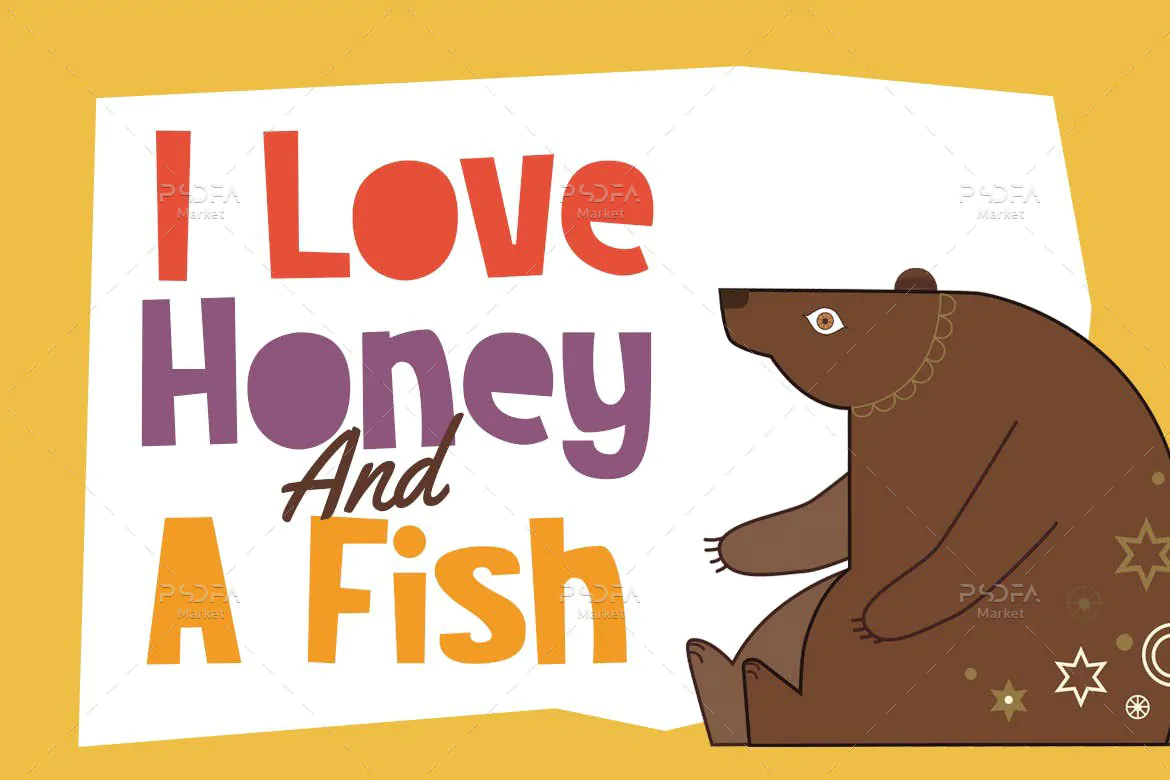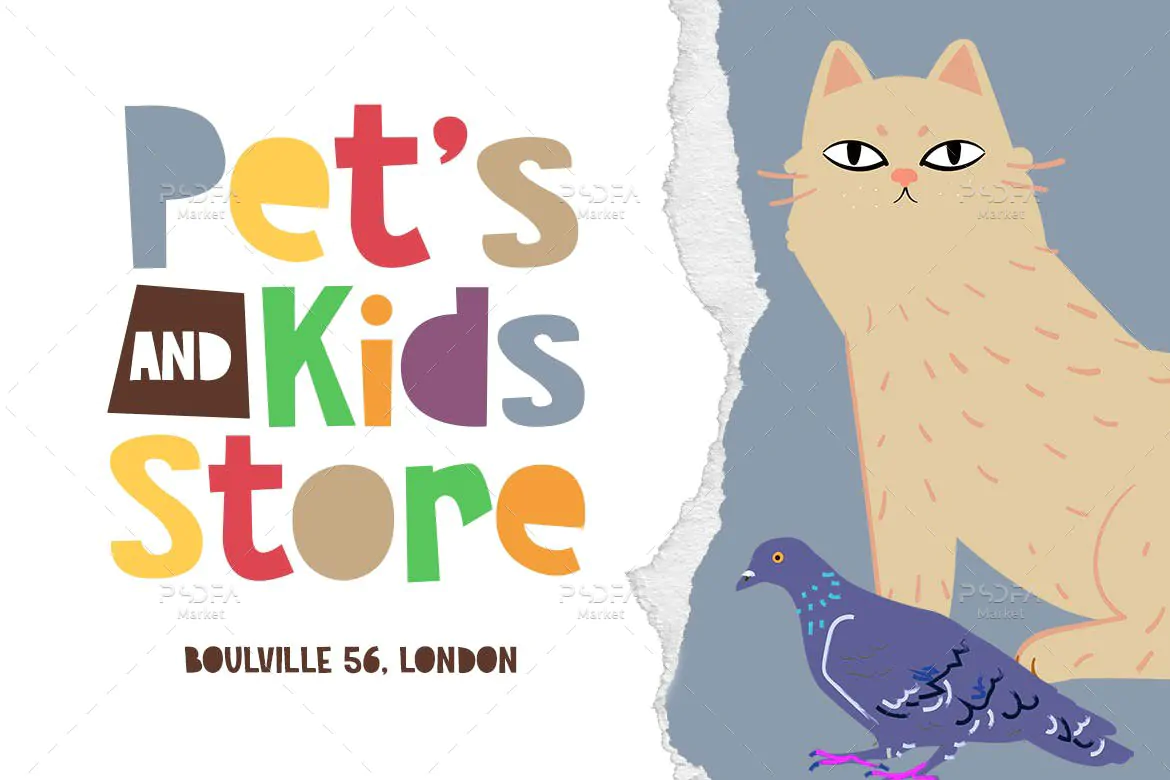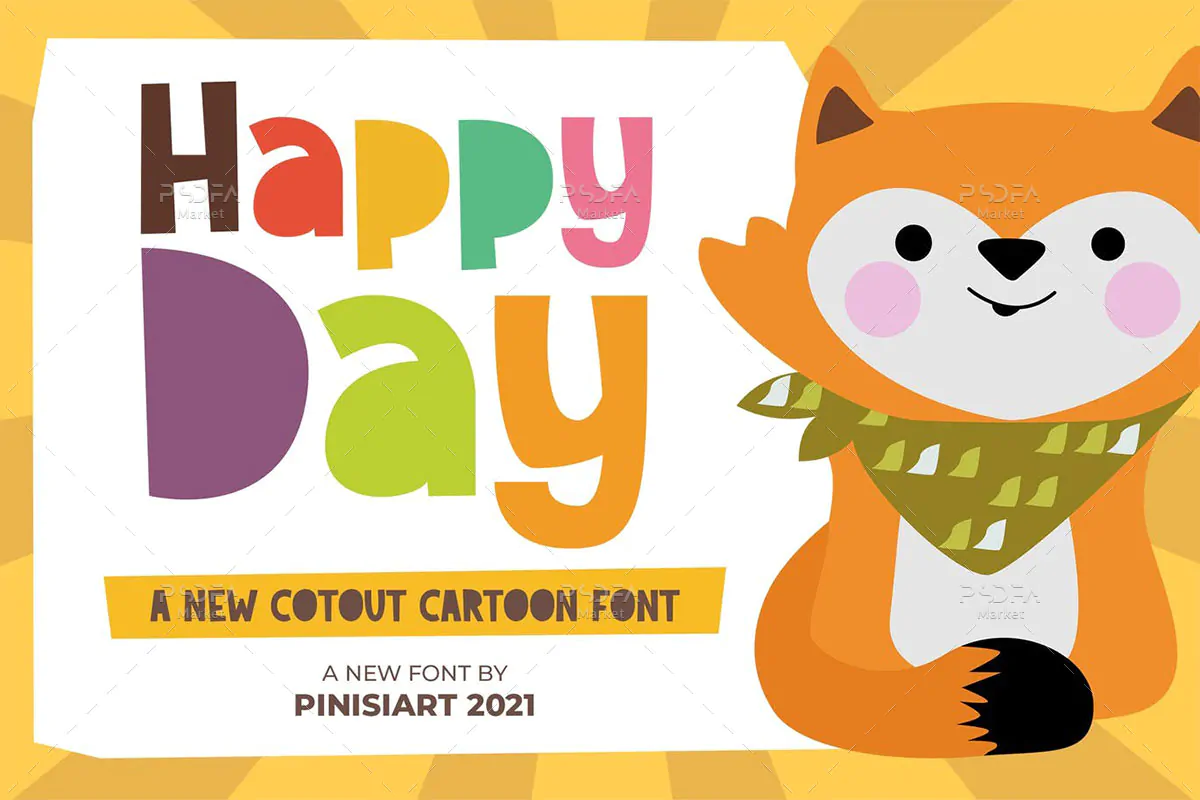
فونت کودکانه کاغذ برش خورده Happy Day
فونت کودکانه کاغذ برش خورده
فونت کودکانه کاغذ برش خورده Happy Day یک قلم نمایشی انگلیسی فوق العاده زیبا به سبک کاغذهای رنگی برش خورده است که مناسب جهت استفاده در طرحهای گرافیکی کارتونی و کودکانه میباشد. فونت Happy Day با وزن معمولی طراحی شده است که میتوانید از آن در طراحی انواع پوستر، بروشور، تقویم، بسته بندی محصولات، اسباب بازی، ظروف یکبار مصرف، لوازم التحریر و … استفاده کنید. همچنین نسخه وب این فونت نیز در فایل محصول قرار دارد که میتوانید از آن در طراحی صفحات وب استفاده کنید.